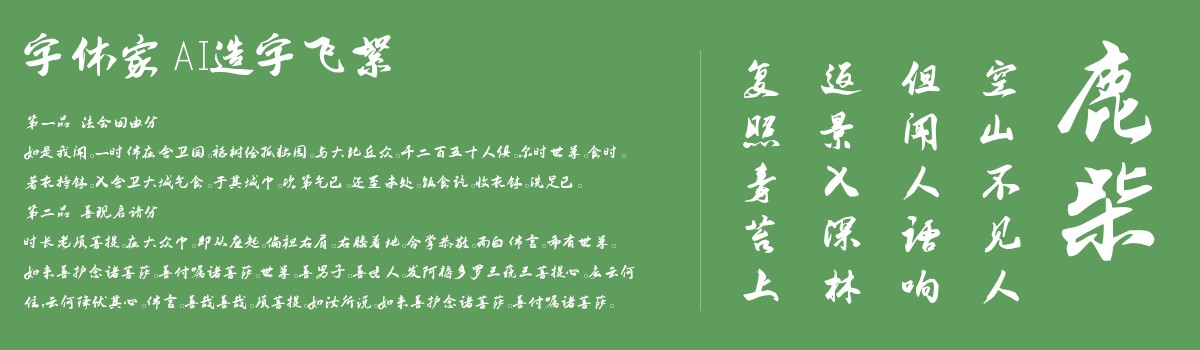
字体家AI造字飞絮
字体家AI造字飞絮是一款由字体家AI神笔造字生成的艺术字体,这款字体带着手写的温度,笔画像浸润墨色的毛笔轻提重按:起笔处有细微顿感,像指尖轻触纸面的初始压力;行笔时线条有自然粗细变化,时而如发丝般纤巧,时而似棉线般饱满;转折处圆润柔和,像水流遇石自然绕开的弧度;收笔偶有轻飘出锋,如尾羽轻扫空气的灵动。整体无刻意棱角,笔画间似有若即若离的呼应,像手写时手腕自然带动的连贯,既有书写的随性,又暗藏结构的稳妥,摸上去该是温润不硌手,像触摸晾晒后的宣纸,带着墨香与柔软的筋骨。适合用于一些广告标题、平面文案、海报标题、网页广告用字的编辑。